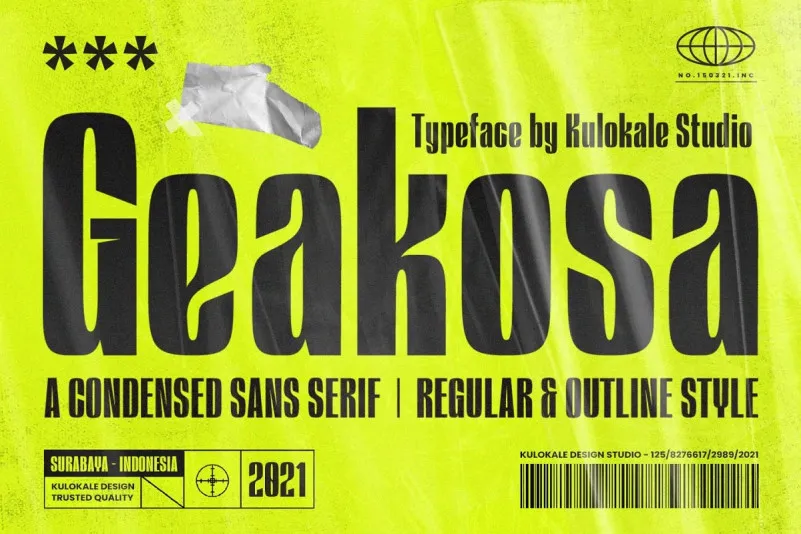
Geakosa Font – Download Grátis
A Geakosa Font é uma escolha perfeita para quem busca simplicidade e força no design visual. Esse tipo de serifada sem guia tem um contraste elevado, criando um destaque imediato em qualquer layout. Esta fonte oferece duas opções de estilo: Regular e Outline Version, garantindo que você tenha flexibilidade para adaptá-la conforme a necessidade do seu projeto. Seja para aplicativos digitais ou impressos, Geakosa traz uma aparência moderna e confiável que se destaca em sua área. Ideal tanto para textos grandes quanto detalhes menores, essa fonte é um recurso indispensável para qualquer designer buscando um tipo sem guia de alta qualidade.